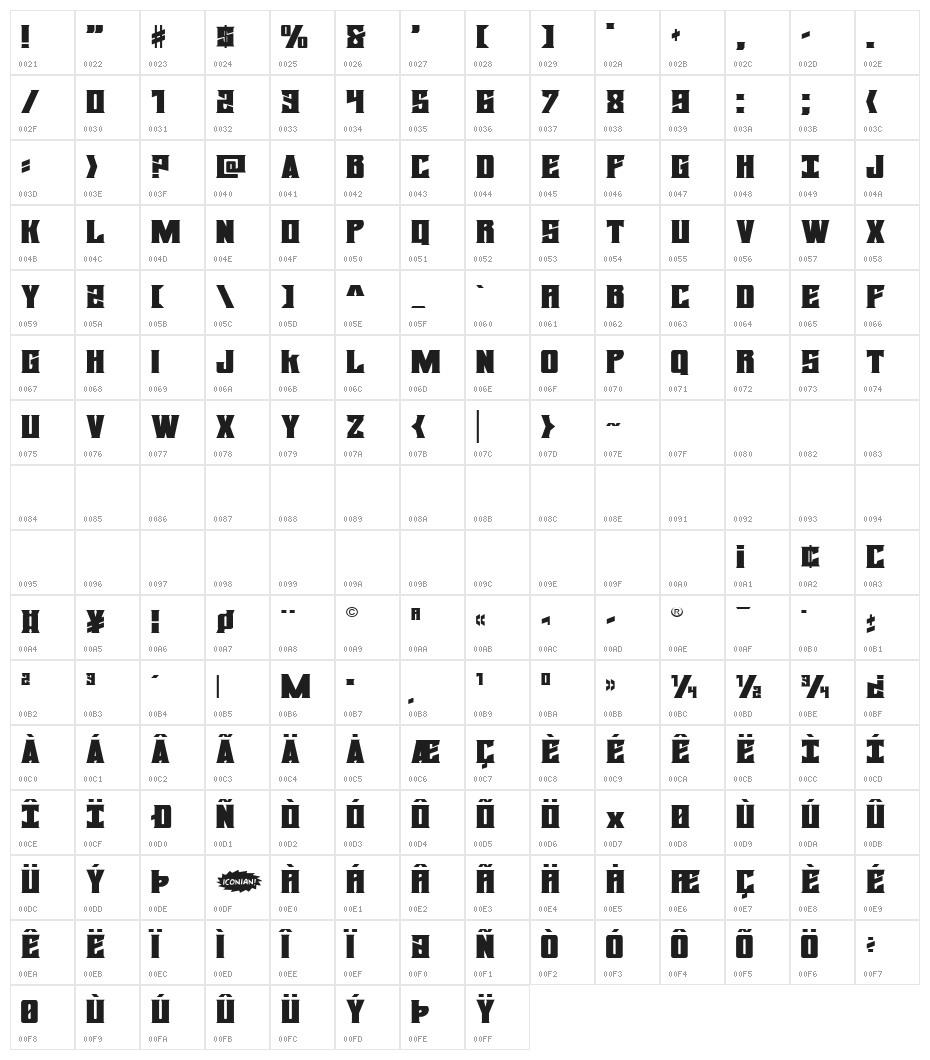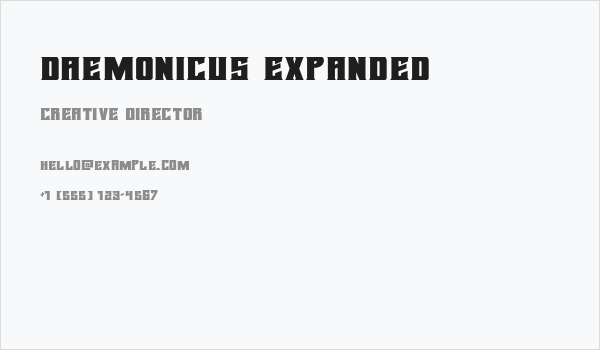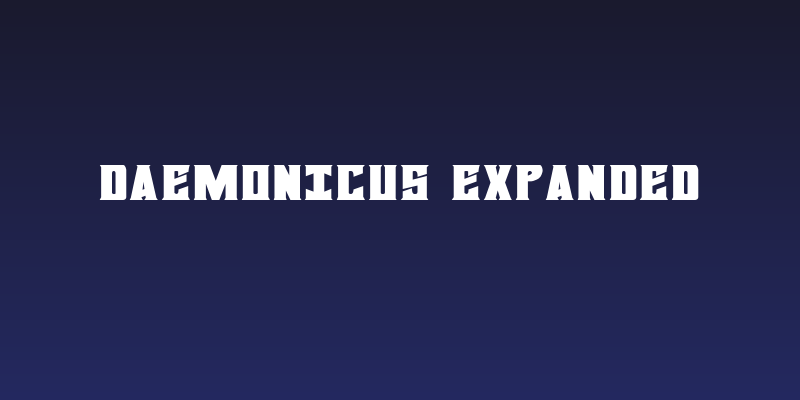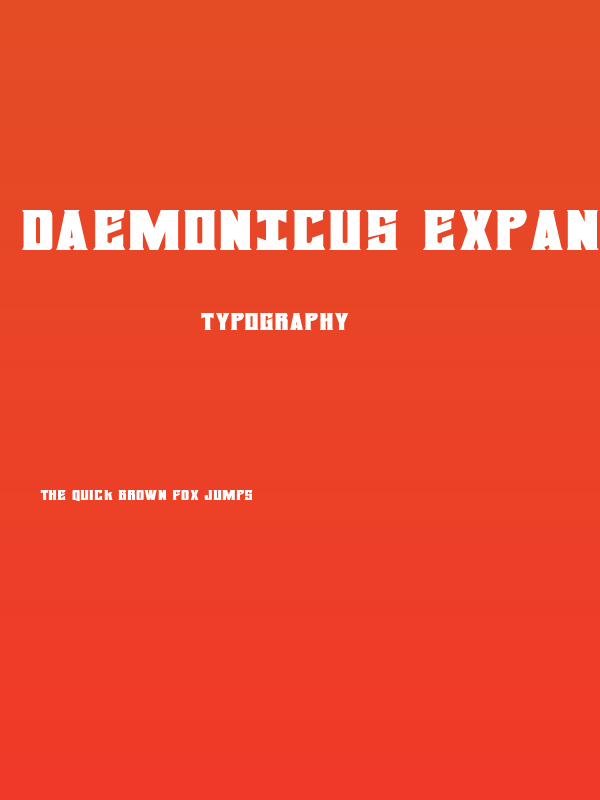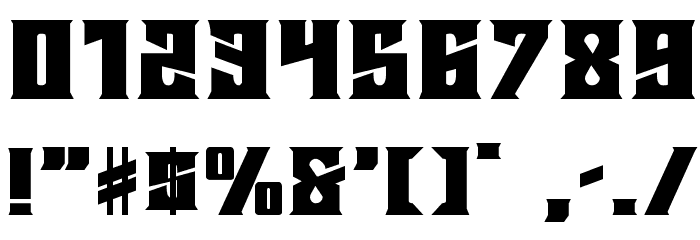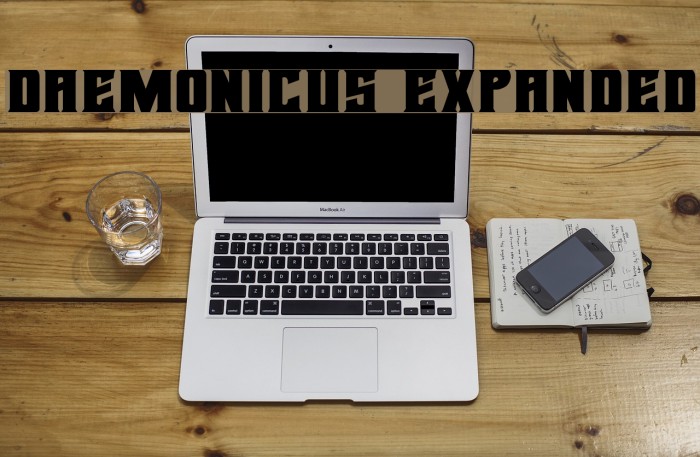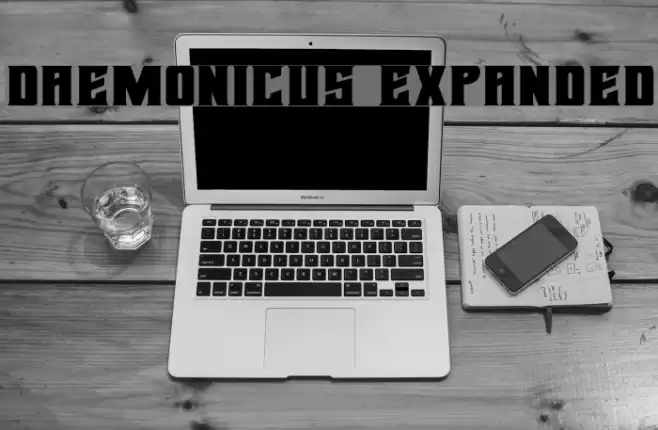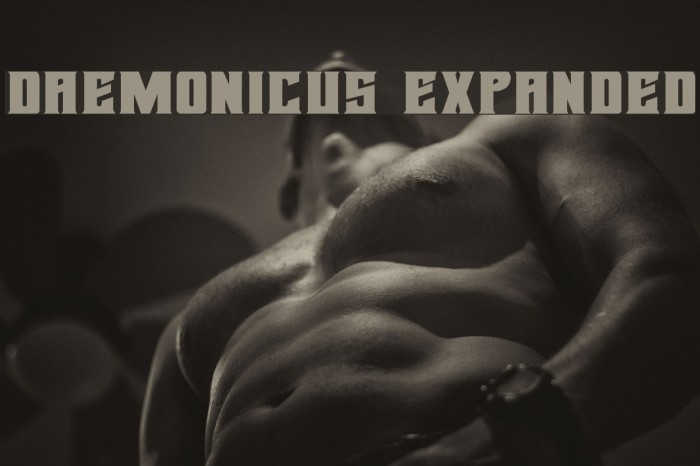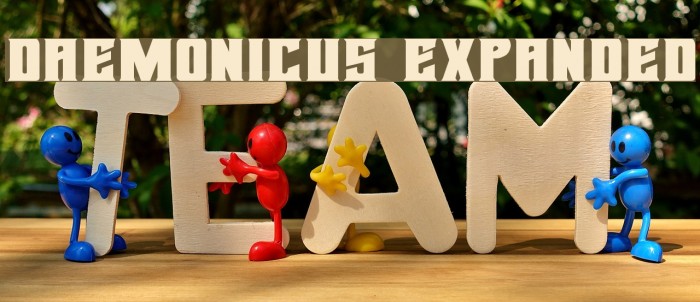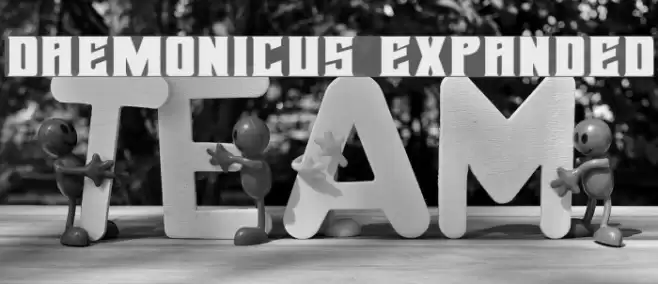
Daemonicus Expanded Font
| Nome | Daemonicus Expanded |
| Peso | Expanded |
| Categorie | Gothic |
| Larghezza | Expanded |
| Stile generale | Gothic, Medieval |
| Progetti proposti | Ideal for projects requiring a strong visual impact, such as posters, album covers, or branding for edgy or alternative products. |